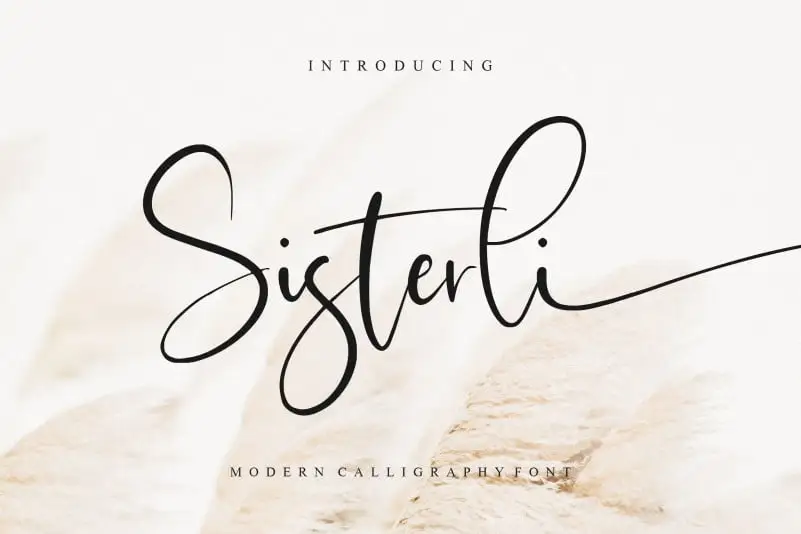
Sisterli Calligraphy Font – Download Grátis
A fonte Sisterli Calligraphy é perfeitamente adequada para diversos projetos criativos no Brasil, especialmente se você busca personalidade e elegância. Suas linhas fluidas e delicadas oferecem uma maneira única de destacar seus designs. Ideal para aplicação em embalagens de produtos, identificação visual de marcas, revistas, redes sociais, convites de casamento ou apenas como forma de expressão ao desenhar letras sobre um fundo, a fonte Sisterli se destaca por sua versatilidade e beleza única. Ela combina perfeitamente com a rica cultura do país, destacando-se em cada projeto gráfico brasileiro. Não importa qual seja seu próximo projeto – embalagens, logomarcas ou até mesmo mensagens de redes sociais, Sisterli é uma escolha inteligente para criar um impacto visual profundo e único.